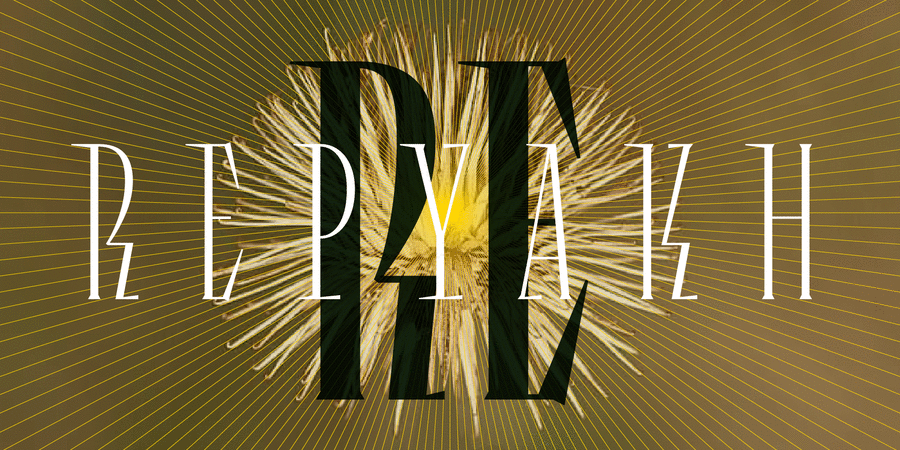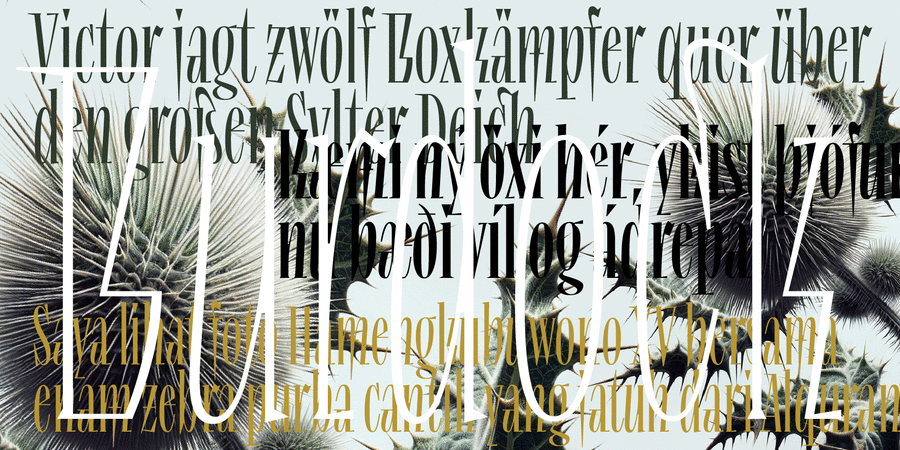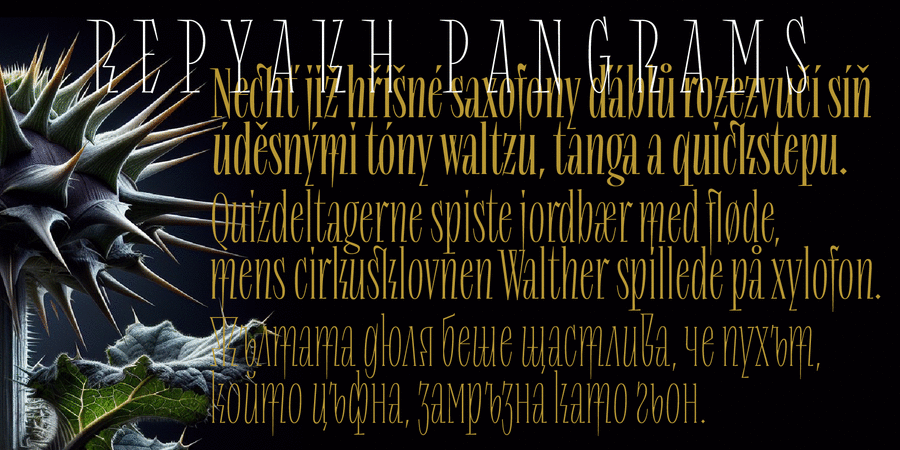
Опис гарнітури RepyakhРеп'ях – це акцидентний варіативний шрифт + 4 накреслення різної ваги. Автори надихалися літераціями відомого українського графіка Миколи Бутовича. Шрифт розробила студія Lev Type у співпраці з Дмитром Растворцевим у 2024 році.
Особливості сімейства шрифтів RepyakhХіт десятиліття:
Асоціації з сімейством шрифтів RepyakhОсобистість і характер гарнітури:
гордий, темпераментний, історичний, самобутній, характерний, оригінальний, різкий, гострий, етнічний, натуральний, традиційний, колоритний, артистичний, художній, динамічний, ностальгічний, ремісничий, виразний, племінний, артізанальний, рукотворний, чіткий, незвичайний, експериментальний, старовинний, якісний, срібний, унікальний, химерний, вигадливий, творчий, крафтовий, осінній, вінтажний, олдскульний, цікавий, дивний, ризикований, грубий, епатажний, ламаний, андеграундний, дикий, колючий, сухий, зухвалий, екзотичний, кричущий, макабричний, радикальний, дотепний, ритмічний, високий, тісний, тонкий, худий, сріблястий, стрункий, дротяний, вільний, мотивуючий, активний, амбітний, добротний, сміливий, консервативний, героїчний, красивий, пафосний, майстерний, урочистий, епічний, дзвінкий, легендарний, вишуканий, жорсткий, авторитетний, переконливий, впевнений, лицарський, естетичний, золотий, кінематографічний, стійкий, хуліганський, екстремальний, емоційний, яскравий, помітний, живий, козацький, вольний, сильний, екстравагантний, агресивний, небезпечний, драматичний, запальний
ремесло, тату, татуювання, історія, музей, театр, реконструкція, хенд мейд, сувенір, етнографія, легенда, література, епос, прикраса, ювелір, мистецтво, антикваріат, художник, туризм, вечір, захід сонця, сувій, мініатюра, графіка, ілюстрація, осінь, тютюн, спеції, перець, текіла, естетика, гравюра, кузня, геловін, кіно, пам'ятник, меморіал, Трофей, нагорода, замок, надгробок, лицар, обладунки, меч, меню, прапор, козак, карти, пейзаж, закуска, чіпси, гетьман, каскадер, екстрим, горілка, отаман, драма Гарнітура асоціюється з віком: